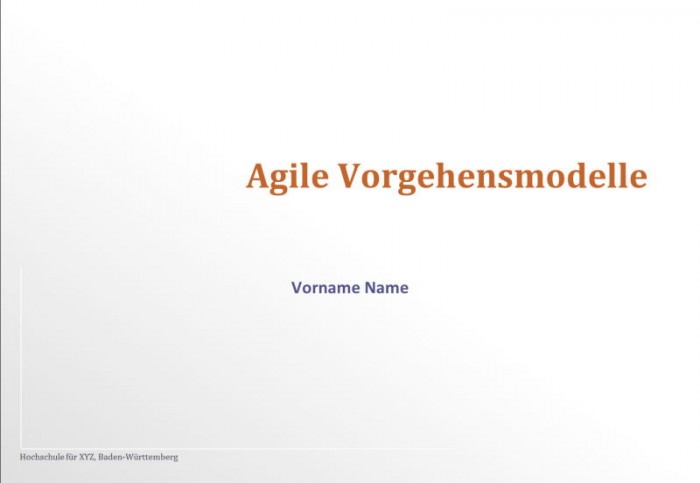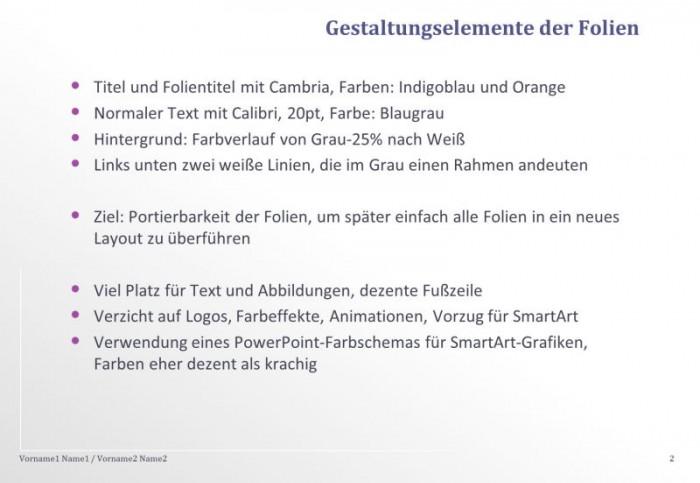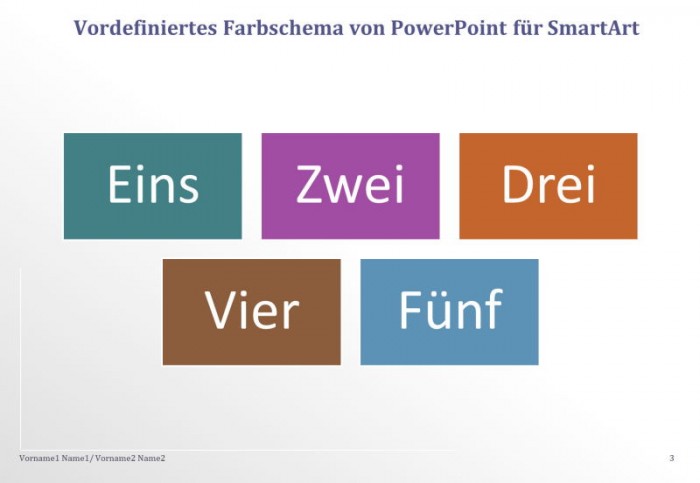
PowerPoint: Eigene Formatvorlage verbessern
weniger ist mehr, dachte ich mir, als ich mir eine Vorlage für PowerPoint gebastelt habe. Mein Ziel war dabei, die vorgegebenen Elemente des Programms zu nutzen, wie z.B. die Folienmaster, Farbschemen, SmartArt-Grafiken, Felder für Fußzeilen und Seitenzahlen - um bei einem Wechsel des Layouts wenig anpassen zu müssen. Die Folien sollten Text/Bild viel Platz lassen, dafür sollten Folientitel und Fußzeile möglichst dezent sein. Einziger Effekt ist der Hintergrund, ein diagonaler Farbverlauf von Grau nach Weiß mit zwei weißen Linien links unten. Beispiele findet Ihr unten. Zielpublikum sind Informatik-Studenten in einer Vorlesung.
Mir gefällt es nicht (mehr). Woran liegt es, was sagen die Experten? Was mir selbst auffällt, bzw. wo ich nicht weiter weiß:
• Am Bildschirm sieht man den Farbverlauf, beim Vortrag mit dem Beamer sieht man fast nichts davon. Ist ein Farbverlauf überhaupt eine gute Idee?
• Die weißen Linien werden ebenfalls verschluckt. Dickere Linien fand ich zu viel. Lieber ganz weglassen?
• Grau, weiß, blaugrau wirkt recht trist, fad, langweilig
• Ich hatte selbst versucht, ein Farbschema zu entwickeln, aber als Laie schnell meine Grenzen entdeckt. Deshalb hatte ich eines der eingebauten Schemen verwendet. Mir kommt es recht soft vor. Wären kräftige Farben heute besser? Was ist denn "Stand der Technik"?
• SmartArts sind eine nette Idee, aber schnell langweilig und von ihren Möglichkeiten eingeschränkt. Jedoch: leicht zu portieren in ein anderes Layout. Ich hatte früher alles selbst mit CorelDraw gezeichnet. Erstens sah man den Grafiken an, daß sie von einem Laien stammen, und zweitens sind sie nur mit Aufwand in ein neues Schema portierbar. Wie macht man das besser, wenn man es selbst macht? (Vermutlich üben, üben, üben ...)
• Die Schriftkombination Calibri/Cambria finde ich ganz in Ordnung. Immerhin wird sie auch in der Fontliste "Schriften für wissenschaftliche Arbeiten" erwähnt. Oder wird die Kombination für PowerPoint schon zu häufig eingesetzt?
Hier die Beispiele:
Titelfolie:
Normale Textseite:
Farbschema im SmartArt-Objekt:
weniger ist mehr
Als präsentierender Student würde ich stets dem Prinzip "form follows function" den höchsten Stellenwert einräumen. Und als Zuhörer mag ich es übersichtlich. Die Folien dienen ja eher als Illustration des Gesagten oder zur vertiefenden Einprägung.
• Am Bildschirm sieht man den Farbverlauf, beim Vortrag mit dem Beamer sieht man fast nichts davon. Ist ein Farbverlauf überhaupt eine gute Idee?
Farbverläufe sind doch out, die sind so Neunziger :)
• Die weißen Linien werden ebenfalls verschluckt. Dickere Linien fand ich zu viel. Lieber ganz weglassen?
Ja. Zumal die Information, an welcher Uni Du bist, im Rahmen Deines Vortrages überflüssig ist. Beim Download würde ich sowieso zum PDF-Format raten.
• Grau, weiß, blaugrau wirkt recht trist, fad, langweilig
Mag sein, doch soll ja die Folie nicht vom Gesagten ablenken.
• Ich hatte selbst versucht, ein Farbschema zu entwickeln, aber als Laie schnell meine Grenzen entdeckt. Deshalb hatte ich eines der eingebauten Schemen verwendet. Mir kommt es recht soft vor. Wären kräftige Farben heute besser? Was ist denn "Stand der Technik"?
Kräftige Farben sind ok, doch sind dabei nur nur die rein physikalischen Gegebenheiten des Seminarraumes zu beachten (direkte Sonneneinstrahlung, schwacher Beamer, farbige Wand, ...), sondern auch die psychische Wirkung: Rot ist zwar gut sichtbar, aber auch eine Signalfarbe.
• Die Schriftkombination Calibri/Cambria finde ich ganz in Ordnung. Immerhin wird sie auch in der Fontliste "Schriften für wissenschaftliche Arbeiten" erwähnt. Oder wird die Kombination für PowerPoint schon zu häufig eingesetzt?
Auf Krampf sich abheben zu wollen, kann bei Powerpoint schädlich werden, wenn die Zuhörer eine Erwartungshaltung mitbringen. Die Schriftwahl sollte imo nur nach Sichtbarkeitsprinzipien getroffen werden.